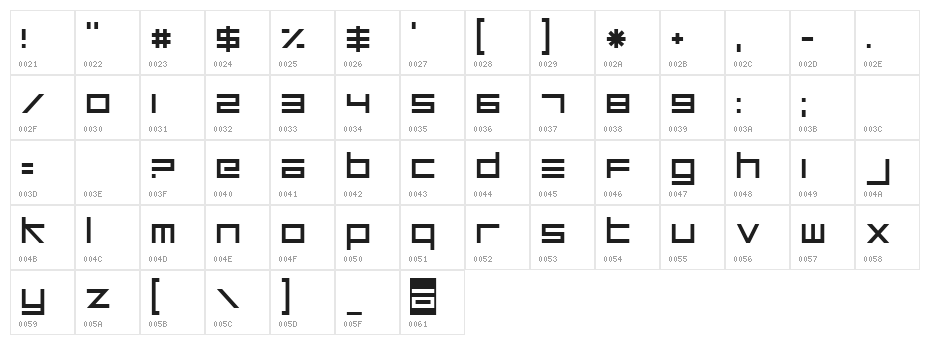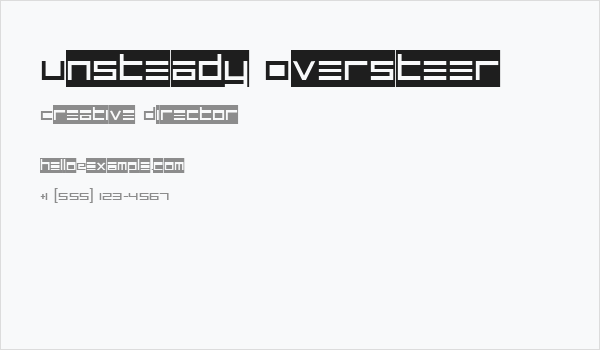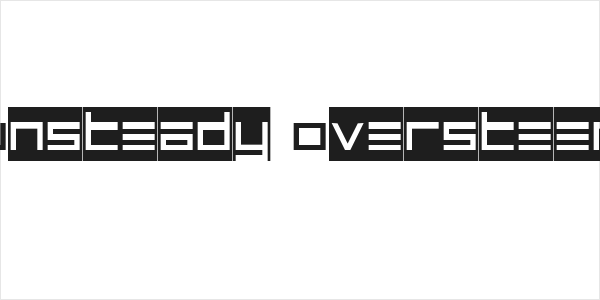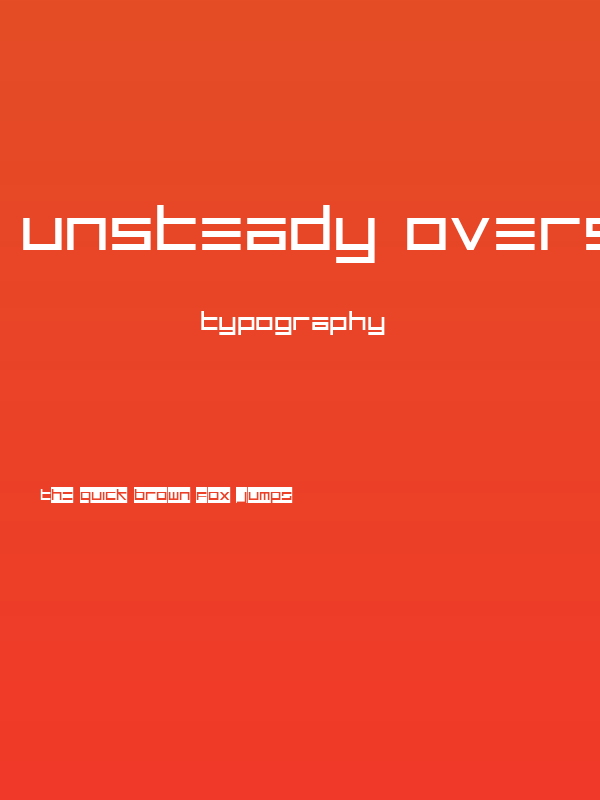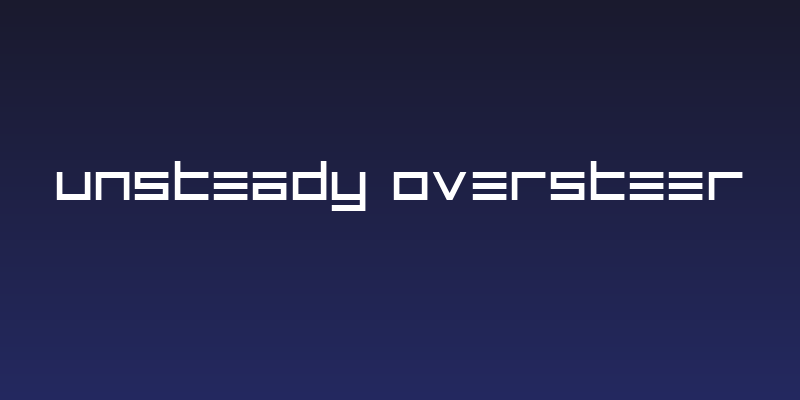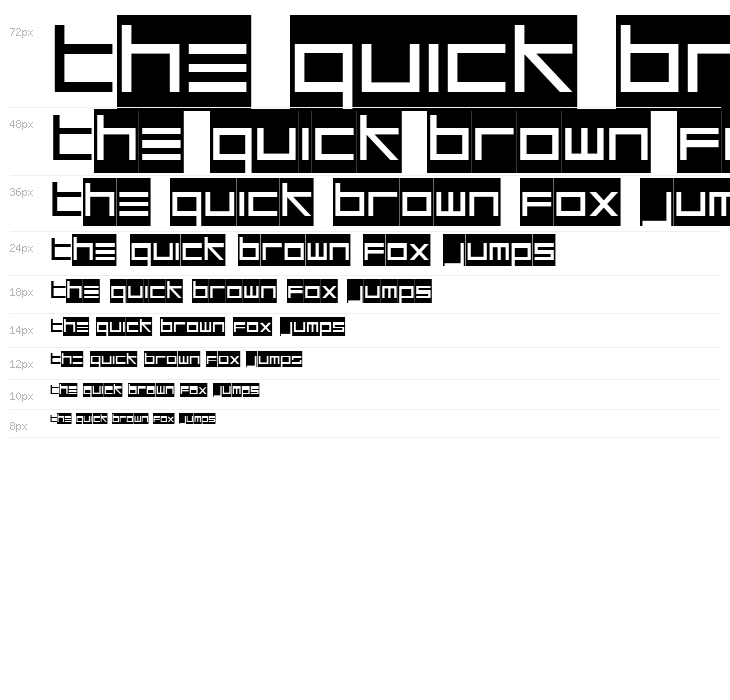
Unsteady Oversteer Font
| Anwendungsfall | Logos, Headlines, Digital interfaces |
| Vorgeschlagene Projekte | Ideal for tech-related branding, video game graphics, digital interfaces, and futuristic-themed posters. |